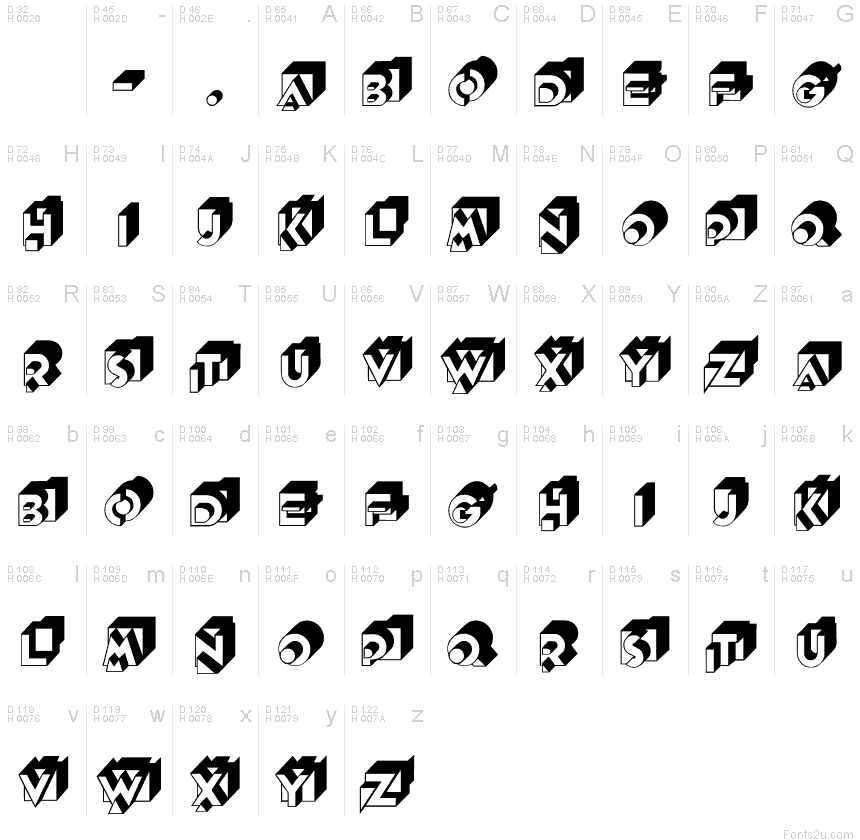
Knockout di Richard William Mueller è un font display 3D gratuito che colpisce con l'impatto di un montante grafico. Ogni lettera sembra scolpita in un blocco solido o in un cilindro, con volumi neri audaci e tagli bianchi netti che sporgono in avanti, come se fossero illuminati dall'interno. Il risultato è sonoro, tattile e pieno di movimento: le lettere non si limitano a sedere sulla pagina, sembrano balzarne fuori.
Usa Knockout per dare un pugno di energia al branding sportivo, ai loghi streetwear, ai titoli di giochi, alle locandine, alle copertine sci-fi o a qualsiasi packaging che richieda un'attitudine immediata. Questo font gratuito brilla nei grandi formati, dove le sue forme scolpite possono respirare; abbinalo a un sans serif pulito e sobrio per il testo principale, in modo che le iniziali 3D rimangano le incontrastate protagoniste.